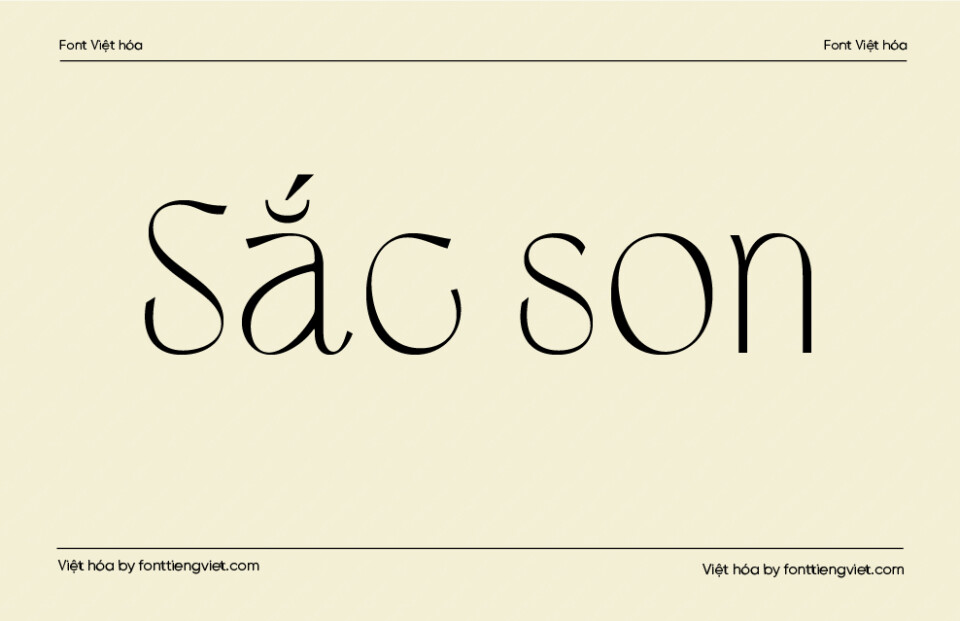
Font Việt hóa 1FTV VIP The Saroja – Đẳng cấp nghệ thuật chữ viết cho thiết kế đồ họaGiới thiệu về Font Việt hóa 1FTV VIP The SarojaTrong thế giới thiết kế đồ họa hiện đại, việc tìm kiếm một bộ Font Miễn Phí nhưng vẫn đảm bảo tính thẩm mỹ và chuyên nghiệp là điều mà mọi nhà sáng tạo đều mong muốn. Font Việt hóa 1FTV VIP The Saroja chính là câu trả lời hoàn hảo cho những ai đang tìm kiếm sự kết hợp giữa nét cổ điển và hơi thở đương đại. Đây là một bộ font chữ thuộc phân khúc cao cấp, được đội ngũ 1FTV chăm chút tỉ mỉ từng đường nét để phù hợp hoàn toàn với bảng mã tiếng Việt, giúp người dùng không còn lo lắng về lỗi hiển thị hay thiếu dấu khi thiết kế các ấn phẩm quan trọng.Nguồn gốc và phong cách thiết kế của The SarojaBộ Font Việt hóa 1FTV VIP The Saroja lấy cảm hứng từ những nét vẽ tay thanh mảnh nhưng đầy nội lực, gợi nhắc đến vẻ đẹp thuần khiết và sang trọng. Tên gọi Saroja thường mang ý nghĩa về hoa sen trong văn hóa Á Đông, phản ánh sự thanh cao và tinh tế. Chính vì vậy, cấu trúc của font chữ này sở hữu những đường cong mềm mại, các nét nối linh hoạt và độ tương phản giữa nét thanh nét đậm cực kỳ hài hòa. Điều này tạo nên một tổng thể thị giác bắt mắt, dễ dàng thu hút sự chú ý của người xem ngay từ cái nhìn đầu tiên.Ưu điểm nổi bật của Font Việt hóa 1FTV VIP The Saroja trong thiết kếLý do khiến Font Việt hóa 1FTV VIP The Saroja trở nên nổi bật giữa hàng ngàn font chữ khác chính là khả năng ứng dụng đa dạng. Dù bạn đang thực hiện dự án thiết kế thiệp cưới, bìa sách, logo thương hiệu thời trang hay các banner quảng cáo sự kiện, bộ font này đều có thể đáp ứng một cách xuất sắc. Sự chỉn chu trong quá trình Việt hóa giúp các ký tự đặc biệt như “ă”, “â”, “đ” hay các dấu thanh được đặt đúng vị trí, giữ nguyên được linh hồn và cấu trúc ban đầu của tác giả thiết kế gốc.Tính tương thích và trải nghiệm người dùngMột điểm cộng lớn của Font Việt hóa 1FTV VIP The Saroja là khả năng hiển thị tốt trên nhiều nền tảng khác nhau. Từ các phần mềm chuyên dụng như Adobe Photoshop, Illustrator cho đến các công cụ văn phòng đơn giản như Word hay PowerPoint, font chữ này đều vận hành mượt mà. Với các bạn học sinh, sinh viên hay giáo viên, việc sử dụng bộ font này trong các bài thuyết trình sẽ giúp nội dung trở nên sinh động và chuyên nghiệp hơn rất nhiều. Độ rõ nét của các ký tự giúp người đọc dễ dàng theo dõi thông tin mà không gây mỏi mắt hay khó chịu.Cách sử dụng và cài đặt Font Việt hóa 1FTV VIP The Saroja hiệu quảĐể tận dụng tối đa vẻ đẹp của Font Việt hóa 1FTV VIP The Saroja, người dùng nên kết hợp nó với những phông chữ không chân (Sans-serif) tối giản ở phần nội dung văn bản. Điều này sẽ giúp tạo ra sự tương phản thú vị, làm nổi bật tiêu đề chính hoặc những câu trích dẫn quan trọng. Việc cài đặt cũng rất đơn giản, bạn chỉ cần tải tệp định dạng .otf hoặc .ttf về máy tính, chuột phải và chọn Install là đã có thể bắt đầu sáng tạo. Hãy lưu ý kiểm tra bản quyền nếu bạn có ý định sử dụng bộ font này cho các dự án thương mại lớn để đảm bảo quyền lợi của nhà thiết kế.Lời kết về bộ font chữ cao cấp The SarojaHy vọng rằng những chia sẻ trên đã giúp bạn hiểu rõ hơn về giá trị mà Font Việt hóa 1FTV VIP The Saroja mang lại cho cộng đồng thiết kế tại Việt Nam. Đây không chỉ đơn thuần là một công cụ gõ chữ, mà còn là một tác phẩm nghệ thuật giúp nâng tầm giá trị cho mọi sản phẩm sáng tạo. Nếu bạn đang tìm kiếm thêm nhiều lựa chọn khác, đừng quên ghé thăm trang web Font Miễn Phí, Font Việt Hóa, Font Việt hóa 1FTV VIP The Saroja để cập nhật những xu hướng chữ viết mới nhất. Hãy để sự sáng tạo của bạn bay cao cùng những nét chữ tinh tế và đầy cảm hứng từ bộ sưu tập này.
Font Việt hóa 1FTV VIP The Saroja